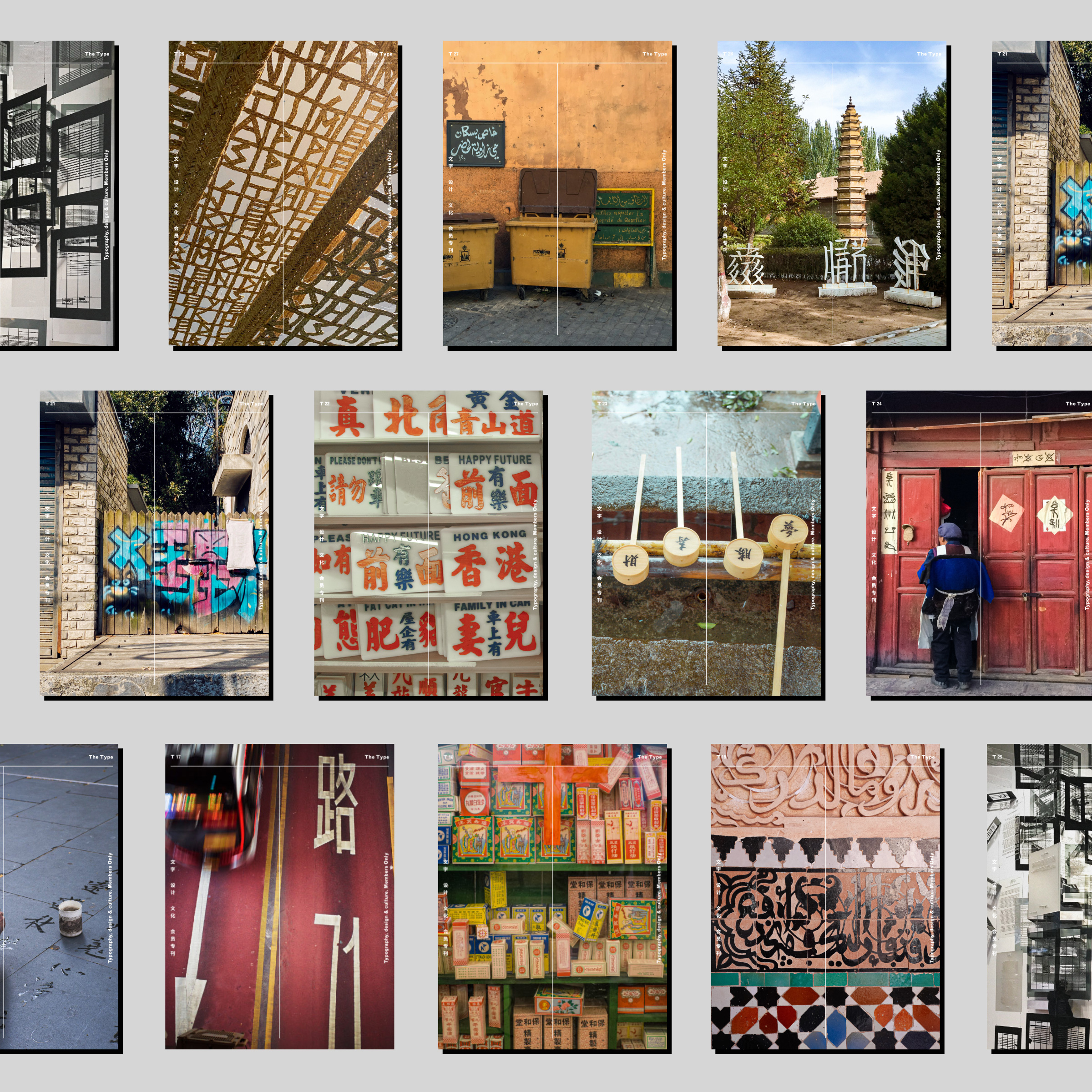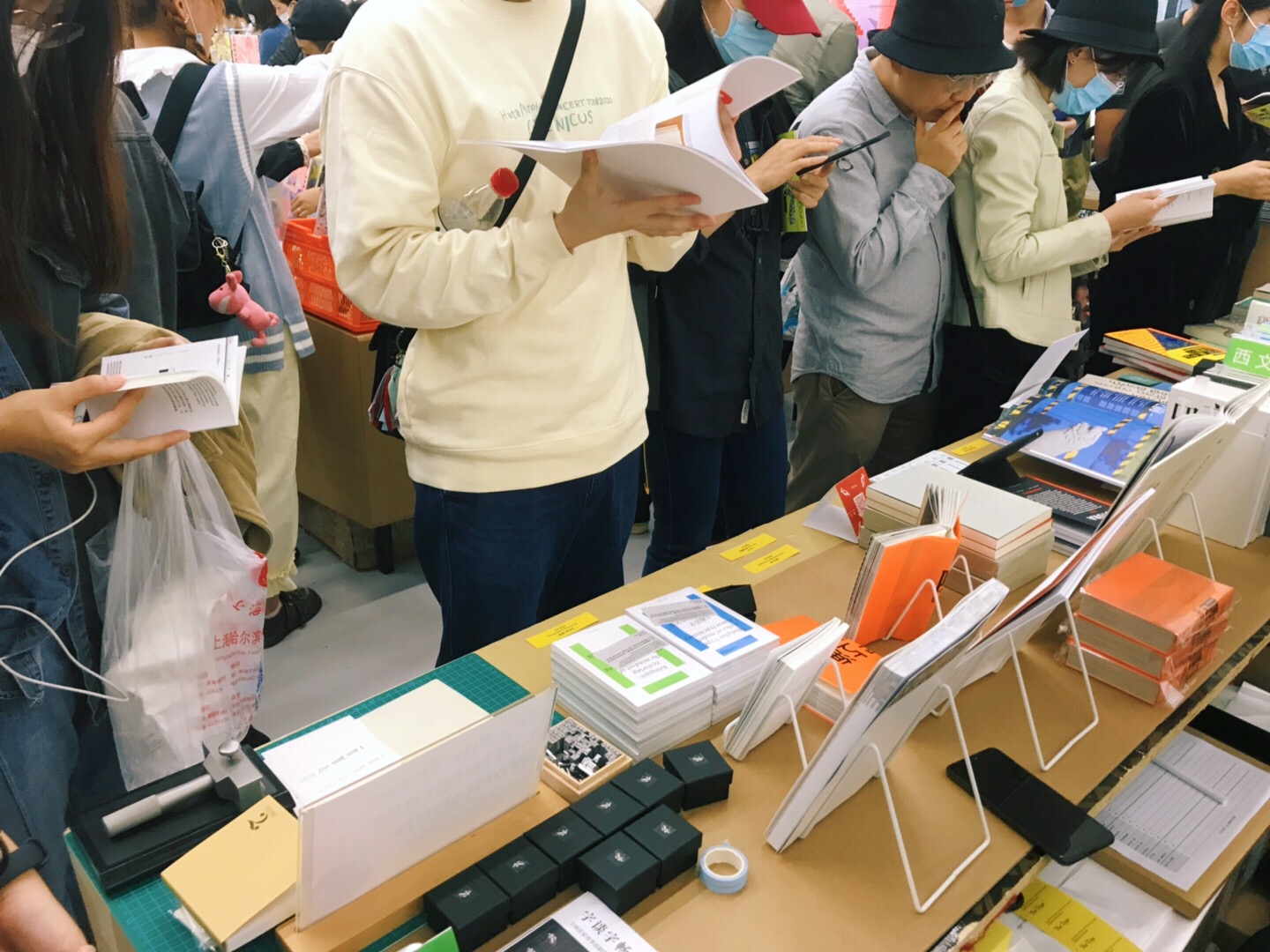
从巨大的不确凿中开始的 2020,仍在不确凿中结束了。漫长的一年中,疫情的反复周折以及东西方社会议题的此起彼伏,淋漓尽致地将今日世界的联结与分裂并行展示在我们眼前。许多事发生了,许多事停下了,许多思考也在酝酿。而思想不应当是一座孤岛,因此在准备跨年小结时,编辑 Mira 把提给团队的问题也抛给了 The Type 的新老朋友们:
2020 给你带来影响的理念和思考是什么?
有什么让你受到了启发?
作答的有设计师,有研究者,也有教育者、写作者、艺术与文化的观察者与构建者。感谢他们平日对 The Type 的支持与勉励,也感谢他们从全球不同角落给我们发来认真的回答。这些对工作、生活和社会的感悟,将陪伴我们一起步入新的开始。
Rex Chen
设计师,The Type 主编,伦敦
2020 年让我体会到稳定的社会和生活秩序有多么不堪一击。个体多年来勉强维系起来平稳的生活方式、各种力量努力形成的社会繁荣,都在短短一年内在世界各地而被逐个、深刻地打破了。这一打破不仅关乎日常活动,无法出门上班,下街吃饭,孩子被固定在屏幕前,老人要面对孤独;也关乎心理的防线,我们要被迫要思考彼此的关系、工作的价值、生活的节奏,连社会认知和政治坐标都急需重判。英国政府应对疫情失法,让我在这种压迫的环境中度过了整年。
与公共机构的怯懦和混乱相比,这一年展现出个体的坚韧、互助和创造力对我而言是不断的亮点。无论是突破限制的公民发声、调查、抗争,还是集中出现的资源调动、社区动员、义务工作,都让人感兴奋和欣慰。艺术设计界也不懈怠:迅速组织起的各地远程艺术书展、丰富有趣的线上设计大会、免费的戏剧音乐会观看平台、各类院校专门开放的学生课程和公共讲座、博物馆和画廊组织的虚拟展览,甚至疫情下拍摄的影片等,以及 The Type 团队大家的努力,都让我在这一年动荡的生活中感到安慰,受到启发,看到希望。
Eric Liu
《字谈字畅》主播,The Type 编辑,东京
对于「不是在机场,就是在去机场的路上」的我来说,2020 魔幻之年尽管改变了行动方式,却丝毫没影响我们在字体排印上的探索、思考和发声。老一辈日本设计师不止一次说过「一款字体的普及总是需要十年的」,而整个字体排印历史的尺度则可达半个世纪直至一个千年。例如在今年的字体赛事中看到的创新作品,其中既有传承神韵的佳作,也不乏疲于模仿的习作,但有了字体排印史的大尺度,就能心平气和对待各种情况,多一些包容也多一些期待。在 W3C《中文排版需求》中,我重点修订了「行首行尾禁则」「行内调整」等在今后几十年对中文排版起到纲领性作用的内容;今年参与的一些系统字体顾问、监修工作,也望对中文读者的日常阅读做出小小的贡献。当然印象最深的还是参与主持全球 ATypI 2020 线上年会,世界各地的文字设计爱好者投入个人宝贵时间、排除万难地全力以赴,让人看到了大会初建时的初心,在焦头烂额的现实世界找回一片纯净天空。
不积跬步无以至千里。在历史大尺度下,才知脚踏实地的写作发声和实践最为重要。在自媒体泛滥的年代,跳票可以成为一种骄傲,甚至「催更」还能成为付费会员专属权益,但我们从不随波逐流,五年以来隔周二播出一期「字谈字畅」播客、两年以来每月一期 The Type 会刊,都从未被各种杂音打乱过脚步。与其说是在锻炼耐力,更应该说这本身就是我们的一种态度。在不断重复的历史长河中,非典新冠都只会是小小花絮,最令人畏惧的其实是停止思考。翻年历,无非只是轻松的一个小动作而已。
Mira Ying
平面设计师,译者,The Type 编辑,上海
有位热爱天文学的朋友曾对我说,人类最宝贵的就是提问,没有回答,只是提问。今年我时常提醒自己这句话。疫情恐慌中,人们渴望回答和承诺;地缘政治角力中,人们追逐预言和指引;消费狂潮中,人们顺从夸大其词而斩钉截铁的营销话术;社会矛盾中,复杂诉求被碎片式的媒介简化成单薄的符号,以便站队。我自己也常渴望确凿的回答,当思考创作者该如何介入公共讨论时,总想寻找某种有效的表达或行为方案,但事实上,无论哪种表达最终都会被话语权市场挪用、收编、消费和稀释。而在整体矛盾加速的今年,这种周期变得更短,暴露得更彻底。
今年读的 Thomas Mullaney 教授的《中文打字机》,其研究主轴就是文字技术革新者们设置题面(puzzle)的路径,而非最后「胜出」的方案。这启发我联想到自己也应该更关注「设题」思路,改变提问方式:创作者该如何建立起内在的生产机制,能源源不断地为公共讨论提供新的语汇?无论是美学的、文学的、技术的还是行为的语汇,其目的不在于解答,而在于触发,在有限的注意力资源下让尚未被稀释的讨论持续更久,这恰恰关系到改变能来临得多快。驱动这种机制的燃料,是人必须深入到社会的细枝末节和繁杂关系中,摆脱认知上的懒惰和洁癖,接受无法盖棺定论提纲挈领的「杂乱历史」(Martha Scotford),也接受非线性的历史观。未来或许的确被取消了(Mark Fisher),然而在非线性叙事中,未来、历史和现在呈交错关系,新旧语汇的定义是模糊多变的、可被循环利用和拼贴的,也因此是无穷的。
厉致谦
多领域研究与设计者,The Type 成员,三言(3type)联合创始人,上海
因为疫情的关系,在家办公、灵活就业开始变得「普遍」和「正常」起来。对于我来说,我早就以这样的方式工作快十年了。连很多大公司和机构也采用了这样的协作方式。很多人开始重新审视工作与生活的关系,开始思考生命与时间的价值。「十五分钟生活圈」概念兴起,越来越多的人向往摆脱缺乏创造力的工具性工作,无疑是新冠病毒带给人类最好的启示。
今年我在字体研究中发现了一个有趣的现象,加上一个机缘,让我有可能在明年参与一件艺术作品的创作,名字暂定叫「两个祖先」。两个祖先是谁?一个是仓颉,一个是古登堡。这两个祖先有什么关系呢?他们共同塑造出了今天我们阅读的中文字体。为什么这样说呢?因为一个发明了用笔书写的汉字;一个发明的技术,让近代中国进入了金属活字时代,并将中文金属活字的技术规范与限制遗留给了数字字体时代。我们今天的中文字体设计工作,与中国第一代字体设计师们在纸上的工作并没有本质的区别。两个祖先的后人今天都在,看似相似的特征下,却蕴藏着不同的 DNA,我们可以如此加以命名——书写逻辑与活字逻辑。
谭沛然
平面与交互设计师,The Type 编辑,西雅图
第一个对我影响颇深的理念是技术政治(Technopolitics),先是去年通过 《鲸鱼与核反应堆》接触到的,它指明了设计中蕴含的政治潜能,以及它具体怎样充当了意识形态载体;而今年研读到的《加利福尼亚意识形态》可谓前者思路的硅谷细化版本,也帮助从事科技行业的我反思日常的设计操作。第二个给我带来冲击的是今年接触到的建筑写作。科林米娜的《X 射线建筑》里揭示的建筑形式与医疗的关系,以及字里行间流露的福柯式生命政治视角,简直是百分百呼应疫情下的社情百态。而在更广的社会层面上,我至今仍在回味塔夫里在《建筑学的理论与历史》中对「操作性批评」的反驳,他破除了很多设计媒体表现出的自我陶醉和粉饰太平,也对我今年的设计写作影响最大。
很多流行的观点试图把设计定义成其他东西的化身乃至衍生品(如「解决问题」「创作」「策展」等)。但接触上述理念和著作后,我发觉设计仍然首先是一种造形的手艺,也就必须面对形式,它是连接设计与其他概念和领域的原点和桥梁。我甚至开始怀疑,二战后欧美社会建立设计职业合理性的过程,正是建立设计形式的审美自律性(autonomy)的过程。我曾一直在问自己怎样才能达到 praxis,即「知行合一」,但觉得它跟我实际的设计思考总有隔阂,如果没有 2020 的新冠疫情和它激起的动荡和抗争,我可能也不会被心酸、愤怒和无力感推动着开始跨越这层隔阂。希望自己能在新的一年里保持这样的动力继续求索,正如 Eric 说的:「我们跑的是马拉松,不是百米冲刺」。
唐煜
阿科米星建筑、那行文化合伙人,上海
我认为将来的世界是个混合的数字孪生世界,当下世界的状态均为过度状态。这有两个层面。第一层面是:这个未来世界,为了在人类感知上实现现实与虚拟的「一致性」,它会以复刻线下模式而存在,同时更会利用虚拟技术强化复刻的虚拟空间。第个二层面是反过来的:利用扩展现实技术在现实世界中投射第一层面内的感知。最终人们不得不接受一个「没有现实」的现实,即一个没有虚实泾渭分明的混合现实。
基于这个想法,在接下来的几十年间(事实上早在互联网产生那一刻已经开始),人类和各种机器,都在越来越快地搬运各种数据到这个孪生世界。今年的疫情则加速了这个状况。而建筑师则需要思考的是这种「混合孪生」的空间需求极其演变。之前我们所研究的「新零售」只是其中一环。
Elon Musk 和增田宗昭给我比较大的启发。他们俩虽然领域不同,而且一个代表未来,一个代表当下和传统,但是他们都是会为了实现一些「不可能的任务」,而耐心地采用中长期、多层面的战略,例如特斯拉之于 SpaceX,以及茑屋之于 CCC。
套套卢(卢涛)
平面设计师,杭州
启示:从负能力到反脆弱。
先说「反脆弱」(Anti-fragile),这个词是纳西姆·塔勒布的一本书名,也是从《黑天鹅》以来他的思考延续,当然「黑天鹅」现在已经成为了一个常用词,比如 2020 就是一只黑天鹅。2020 的不确定性往往让我们猜想这是另一个 1914?还是 1933?或者 1968?捉急……
在疫情期间我听到了「负能力」(negative capability)这个说法,这是载于济慈的一封信中,指的是一个人身处不确定、神秘、疑惑之中,却并不着急寻求事实和理由。或者说不 judge,万维钢老师用了一个更高级的对应词叫「诛心」,我们往往站在一个道德(民主/现代)高地怒斥:「其心可诛」。在湍流的新冠、选票面前,任何捉急的 judge 都显得刻舟求剑了,所以回到设计而言只要具有时代气息就好,千万不要锚定什么(历史/流派/风格)。
在面对不确定性时,塔勒布告诉我们要勇于拥抱不确定性——因为越是在一方面冒险,就越是会回馈到其他方面的稳定性。这是一种免疫。不确定性的时间窗口是多么的珍贵,一个人的二十到三十岁,新文化运动兼容并包的初期。一旦确定了,只剩下房贷或革命了。
借用塔勒布式的反脆弱养生法,所以我们最好:
A.偶尔搬重物或倒立
B.从甲地到乙地时常变换路线或交通方式
C.每周饿一到两顿
郑初阳
多文字研究与设计师,杭州
最大的思考首先是认识到事情不是简单联系,而是复杂交织在一起的。但我们的思维却是需要有一个航标才能进行思考,再而进行设计创作。比如说,设计这个词不能独立存在,而是需要有一个承载的主体,人无法思维一个没有主体的设计。所以我们的思维就是一种标定主体的方式,而标定主体恰恰需要明确,这样就需要划清事物的边界,某种意义上,是一种简单划分,而无法表述复杂。其次,在这个基础上,人们会发现其实第一步就走错了,在定义事物的同时,已经是一种虚无主义,好比我们的电脑系统里有一个快捷方式,但此快捷方式却不指向任何实际的文件,那么基于此快捷方式所参与的任何设计,也是空无一物的。
我从《利玛窦中国札记》一书受到启发。几百年前的中国,我们从今天看,又近又远。而看利玛窦也是,有时候觉得他像今天的一些中国人一样。
张弥迪
文字与书籍设计师,聿书堂创始人,杭州
米拉问我,此一年将尽,有何感想?思来想去,不知从何说起,这一年来心境变得悲观了一些,不愿多说。生活需要继续,要勇往直前,正所谓「凡心所向,素履以往。生如逆旅,一苇以航」。这不是鸡汤,这是鸡血。
说回正题,作为一个设计师,在今年七月参与「今日重读《今日文字设计》」活动的过程中,让我对文字设计(typography,或称字体排印)有了更深一步的学习和理解,更加坚定地相信赫尔穆特·施密德所说的「我们需要能够符合时代气息的字体,但是首先需要设计师们优雅而庄重地使用字体。」这让我的设计理念变得更加保守,这样好像显得不够高明,尤其是在这个大谈创新的时代。
我们全程参与报道了 ATypI 2020 国际文字设计大会。ATypI 首次举办五天 24 小时不间断的线上全球会议,内容超前丰富。虽然演讲视频还未公布,但通过我们的每日简报、播客访谈和会刊特稿,即可了解大会亮点和全球文字设计领域的最新研究。
世事难料,我们也有很多没做完的事情。例如 TypeTour 旅行计划再次泡汤,一些翻译和出版计划延长了筹备时间,但这也意味已经有许多值得期待的项目已经在 2021 展开,希望能够在新的一年从容呈现给大家。